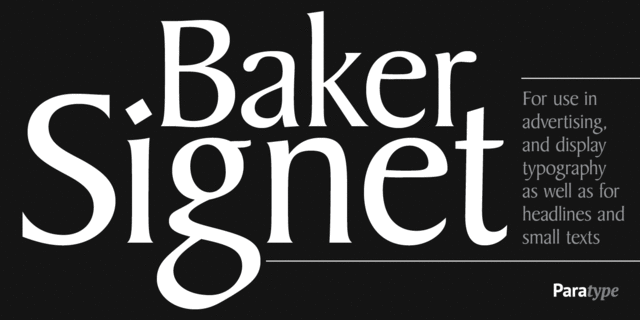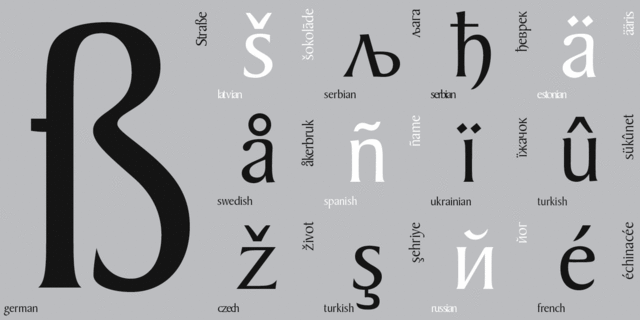
Опис шрифта Baker SignetВерсия фирмы Битстрим шрифта Бейкер Сигнет, созданного известным каллиграфом Артуром Бейкером для компании VGC в 1965 году. Шрифт классических форм с тонким, но эффектным каллиграфическим оттенком и едва наметившимися засечками на концах штрихов. Предназначен для титульных и акцидентных работ, рекламы и набора небольших текстов. Кириллическая версия разработана Евгением Садко и выпущена фирмой ПараТайп в 2008 году.
Особливості сімейства шрифтів Baker SignetХіт десятиліття:
Хіт 1960-х Схожий на шрифти з логотипів, ігор, фільмів:
Близький історичний оригінал:
Baker Signet підтримує 60 мовУкраїнська, Англійська, Німецька, Португальська, Іспанська, Французька, Російська, Голландська, Італійська, Шведська, Фінська, Білоруська, Сербська, Болгарська, Естонська, Албанська, Африкаанс, Баскська, Бретонська, Валенсаска, Galician, Гельська (Шотландська), Данська, Індонезійська, Ірландська, Ісландська (Win), Каракалпацька, Каталонська, Норвезька, Окситанська, Ретороманська, Самі Лулі, Тсванська, Узбецька (Лат.), Фарерська, фризька, Чаморро, Естонська (Win), Південносаамська, Абазинська, Аварська, Агульська, Адигейська, Даргинську, Інгуську, Кабардино-Черкеська, Кабардинська, Карачаєво-Балкарська, Кумицька, Лакська, Лезгинська, Македонську, Мордовсько-Мокшанська, Мордовсько-Ерзянська, Ногайська, Рутульська, Табасаранська, Татська, Цахурська, Чеченська Функції сімейства шрифтів Baker SignetЗастосування гарнітури у верстці:
обкладинка, плакат, афіша, журнал, запрошення, етикетка, пакування, меню, візитка, титул, меморіал, диплом, грамота, пам'ятник, молитвослов Адаптованість гарнітури до носіїв:
Асоціації з сімейством шрифтів Baker SignetОсобистість і характер гарнітури:
дорогий, елітний, благородний, традиційний, якісний, майстерний, культурний, естетичний, витончений, розкішний, художній, знаменитий, дорогоцінний, унікальний, оригінальний, добірний, красивий, комільфо, багатий, сексуальний, джентльменський, фантастичний, пафосний, старовинний, історичний, імперський, сакральний, прекрасний
мистецтво, художник, музика, архітектура, скульптура, опера, поезія, косметика, здоров'я, краса, їжа, алкоголь, коньяк, преміум, ресторан, готель, шоколад, прикраса, ювелір, срібло, коштовності, сервіровка, розкіш, віскі, мода, фарба, пам'ятник, гігієна, чистота, чай, годинник, комільфо, кава, меморіал, живопис, Трофей, нагорода, бутік, концерт, Біблія, вино, захід сонця, філософія, люкс Гарнітура асоціюється з віком: